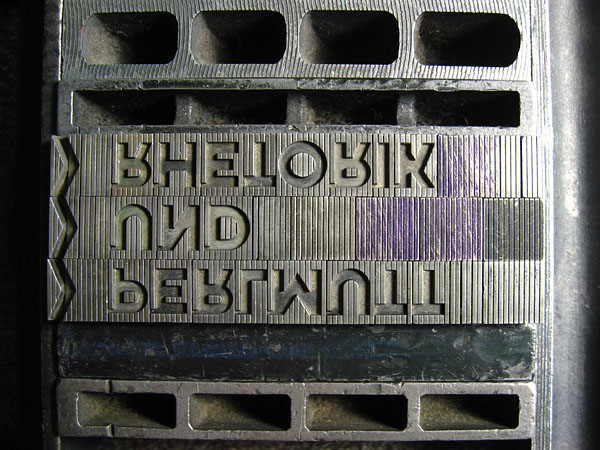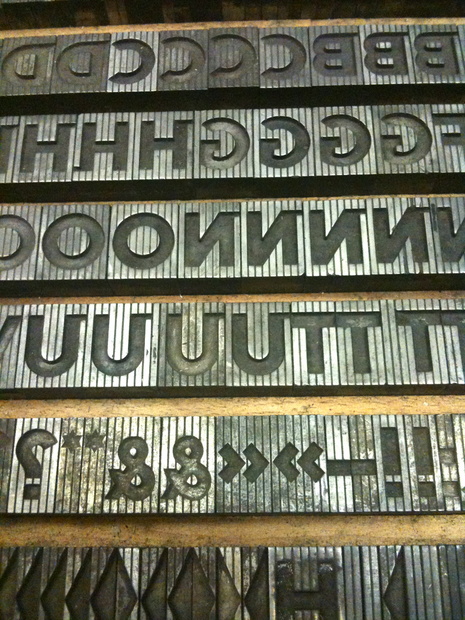
Name dieser Bleisatzschrift
kennt ja jemand von euch den Namen dieser Bleisatzschrift?
Ja, das sind die Schaefer-Versalien.
ich bin derzeit auf den Spuren meines Großvaters K. H. Schaefer. Er hat die Schaefer-Versalien entworfen. Ich habe ihn nie kennengelernt. Da ich weder Drucker noch Grafiker bin, würde mich interessieren, wo man solche Bleisätze kaufen kann? Mein Vater hat leider nur noch Druckerzeugnisse aufbewahren können. An Bleisatzbuchstaben hätte ich sehr großes Interesse. Vielen Dank für Deine Hilfe vorab.